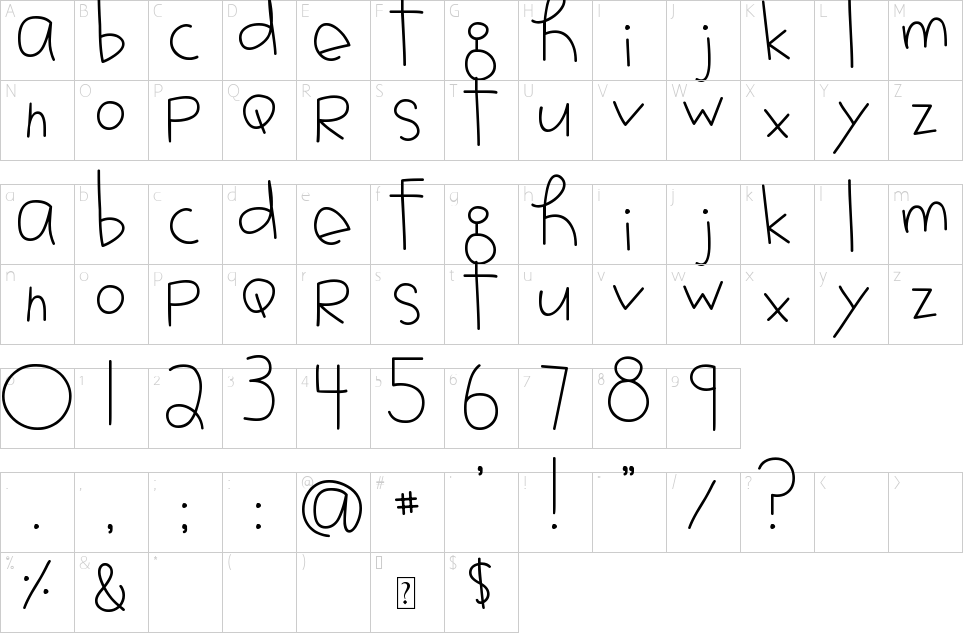
Descubra a MTF Jotted font, uma elegante e versátil opção para personalizar seus documentos e criações digitais. Desenvolvida pela designer desconhecida Miss Tiina Fonts, essa fonte casual e gráfica é perfeita para escrita de cotovelos ou qualquer outra aplicação onde você deseja adicionar um toque minimalista e confortável à sua escrita. Possui uma aparência elegante e fluida, tornando-a uma escolha excelente para criações em ambientes tanto para escrita de cotovelos quanto para o uso em postagens de redes sociais ou criação de designs gráficos. Com seu design agradável e fácil de ler, a MTF Jotted font é uma fonte ótima para aqueles que desejam dar um toque personalizado a seus trabalhos sem comprometer a legibilidade. A MTF Jotted font é uma opção gratuita, disponível tanto para Windows quanto para Mac, e já foi baixada 3.652 vezes. Descubra por que essa fonte se tornou tão popular entre criadores de conteúdo e designers digitais.